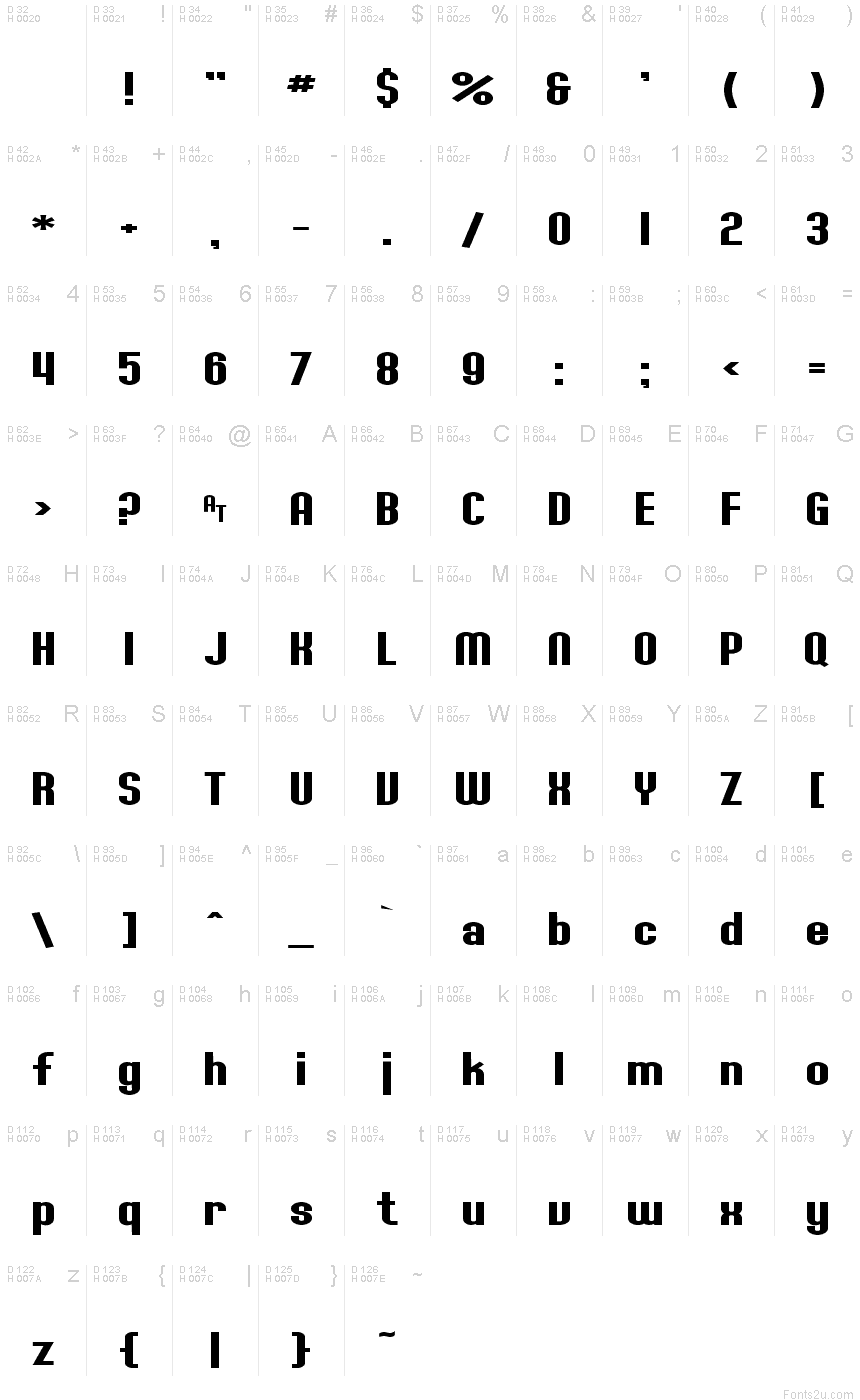
يُعد خط SF Willamette Extended Bold من ShyFoundry خطاً هندسياً مجانياً بلا زوائد، يتميز بتصميم كتلي وصوت جريء يذكرنا بعصر الملصقات الإعلانية. تم بناء الحروف من كتل عمودية ضخمة ومنحنيات مربعة، مما يمنح الخط إيقاعاً مدمجاً وقوياً يبدو مباشراً ومؤثراً بدلاً من أن يكون دقيقاً أو متكلفاً.
يناسب هذا الخط هوية العلامات التجارية لملابس الشارع، والملصقات الموسيقية، والرسومات الرياضية، والتغليف، والعناوين البارزة، خاصة في المواقف التي تحتاج فيها بضعة أحرف فقط لإحداث فرق. وباعتباره خطاً مجانياً، فهو مثالي أيضاً لبطاقات العناوين، والنصوص القصيرة، وشعارات الأحرف المتداخلة (المونوغرام)، لأن أشكاله العريضة وزواياه المقصوصة تتماسك معاً لتشكل تصميماً غرافيكياً قوياً.